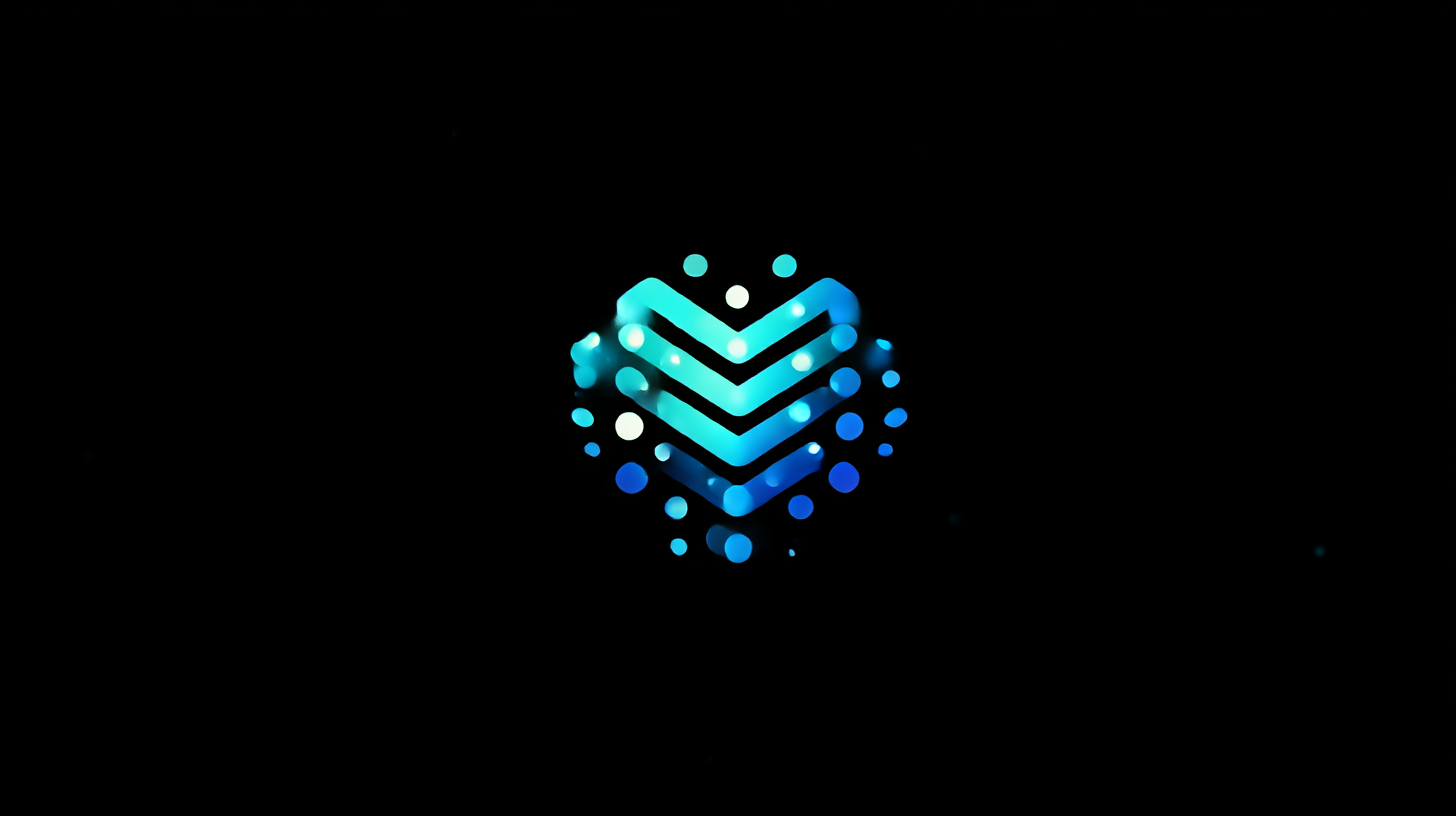
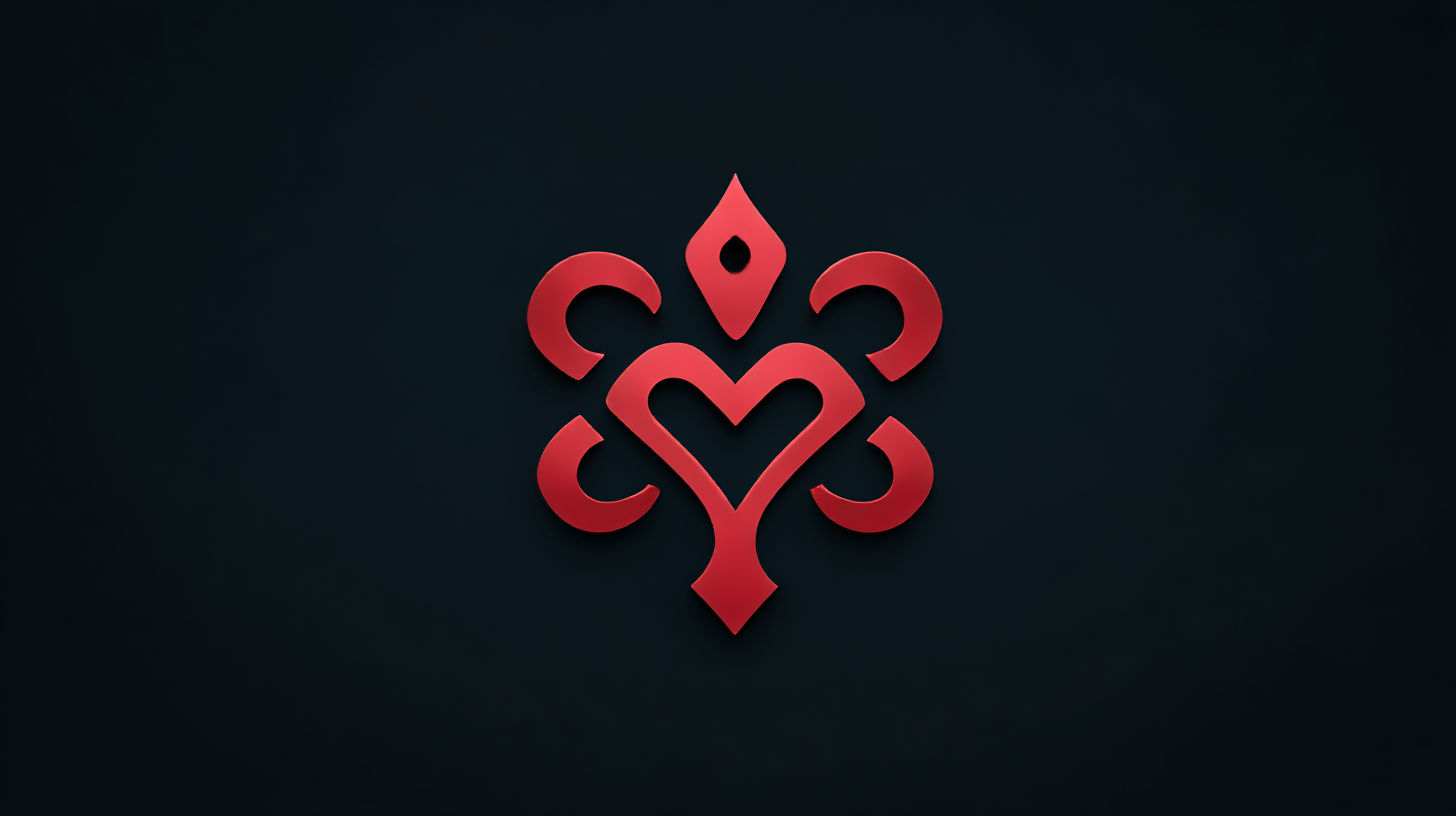
AI로 완성한 내 브랜드 로고 제작기 브랜드를 시작하려면 가장 먼저 떠오르는 게 로고예요. 감각적이고 기억에 남을 로고 하나로 브랜드 이미지가 확 달라질 수 있거든요. 그래서 저도 나만의 로고를 만들기로 결심했답니다. 그런데 문제는 디자인 경험이 전혀 없었다는 점이었어요.
고민 끝에 저는 AI의 힘을 빌리기로 했어요. 요즘은 디자이너 없이도 인공지능을 활용하면 퀄리티 있는 결과물을 만들 수 있다고 해서 시도해봤죠. 이 글에서는 제가 어떤 과정을 통해 브랜드 로고를 완성했는지, 그리고 AI가 어떻게 도와줬는지를 낱낱이 공개할게요! 🎨
이제 본격적으로 각 단계별 과정을 소개할게요. 로고 제작이 막막했던 분들이라면 제 경험이 큰 도움이 될 거예요. 그럼 같이 AI 디자인 여행, 시작해볼까요? 🖌
🎬 브랜드 로고 제작의 시작
처음 브랜드 로고를 만들겠다고 결심한 건, 제 사업 아이디어를 시각적으로 표현하고 싶어서였어요. 이름은 정했지만, 그에 어울리는 이미지를 떠올리는 건 생각보다 쉽지 않더라고요. 색깔은 어떤 톤이 좋을지, 심볼은 넣을지 말지조차 고민이 됐죠. 저는 미니멀한 감성을 좋아하긴 했지만, 너무 밋밋한 건 또 싫었어요.
그래서 로고 제작 웹사이트부터 유튜브 강의, 블로그 후기까지 정말 많은 자료를 찾아봤어요. 그리고 한 가지 확신이 생겼죠. 나 혼자 하긴 어렵겠다... 그때 눈에 들어온 게 바로 AI 로고 생성기였어요. 😲
AI 툴은 정말 다양했어요. Canva, Looka, Hatchful 등 몇 가지를 시도해보며 각각의 특징을 파악했죠. 간단한 설문을 통해 브랜드 성격을 입력하면 자동으로 여러 시안을 보여주는 방식이었어요. 첫 느낌은 "오, 이거 되게 괜찮은데?" 싶었답니다.
로고 스타일을 선택하고 나니, 색상 조합, 글꼴, 아이콘 등이 AI에 의해 제안됐어요. 그중 일부는 제가 상상하지 못한 창의적인 구성이기도 했고요. 이건 진짜 사람의 감각을 뛰어넘는다는 생각이 들었죠. AI랑 협업하는 기분이었어요. 🤖
🧠 사용한 AI 디자인 툴 비교표
🤖 AI가 도와준 창작 과정
로고 제작을 위해 Looka에 접속하자마자, 브랜드 이름을 입력하고 어떤 느낌의 브랜드인지 묻는 설문이 나왔어요. 선택지에는 ‘친근함’, ‘전문성’, ‘모던함’ 같은 키워드들이 있었고요. 저는 브랜드의 방향에 맞게 ‘따뜻함’, ‘신뢰감’, ‘세련됨’을 고른 다음, 색상도 고유 톤으로 블루 계열을 선택했어요.
그다음, AI는 30개 이상의 로고 스타일을 자동으로 추천해줬어요. 이 중에서 제 눈에 띈 건 둥근 텍스트에 간단한 아이콘이 포함된 로고였어요. 너무 화려하지 않으면서도 기억에 남는 디자인이라 첫 느낌부터 확 끌렸죠. 그걸 기준으로 몇 가지 다른 스타일도 섞어봤어요.
Looka는 선택한 로고를 기준으로 자동 조정 가능한 기능도 있었어요. 예를 들어, 텍스트 간격이나 아이콘 크기, 색상 톤의 채도를 미세하게 조정할 수 있었는데 이게 은근히 큰 차이를 만들어내더라고요. 디자인 감각이 없어도 시각적으로 딱 맞는 느낌을 고르기 좋았어요.
로고가 거의 완성된 이후엔 다양한 형태의 적용 예시도 보여줬어요. 명함, 웹사이트, 모바일 앱, 티셔츠 등에서 이 로고가 어떤 느낌으로 보일지를 실시간으로 확인할 수 있었어요. 이건 진짜 놀라운 기능이었고, 마치 실제 브랜드 오너가 된 것 같은 기분이 들었죠. 😍
🎨 AI 자동 추천 디자인 스타일 예시
스타일 설명 적용 예 미니멀 간결하고 직관적인 구성 IT, 패션 브랜드 빈티지 복고풍과 수제 느낌 강조 카페, 공방 타이포그래피 폰트 중심 디자인 출판사, 미디어 심볼형 로고 아이콘 강조 앱, 스타트업 이런 다양한 스타일 중에서 저는 ‘심볼형 + 미니멀’을 조합해서 최종 콘셉트를 잡았어요. 너무 화려하지 않으면서도 브랜드 정체성이 분명해 보여서 딱 좋았어요. AI 추천이 없었다면 이런 조합은 상상도 못했을 거예요. 이게 바로 기술의 힘이겠죠? 💡
🎯 디자인 요소의 선택 기준
AI가 제시해준 여러 로고 중에서 마음에 드는 스타일을 정한 후, 이제는 세부 디자인 요소를 하나하나 직접 조정해 나갔어요. 가장 먼저 선택한 건 폰트였어요. 브랜드의 느낌을 잘 살리려면 글자체가 정말 중요하거든요. 너무 각진 글꼴은 차가워 보이고, 너무 둥근 글꼴은 전문성이 떨어질 수 있었죠.
그래서 여러 번 테스트해보면서 ‘둥근 고딕체’ 계열을 최종 선택했어요. 딱딱하지 않으면서도 깔끔한 인상을 줄 수 있었거든요. 그리고 색상은 브랜드 톤에 맞춰 블루와 그레이 조합으로 조정했어요. 블루는 신뢰와 안정감을 상징해서 특히 금융이나 기술 분야에서 자주 쓰이기도 하죠.
심볼도 고민을 많이 했는데, 추상적인 아이콘보다는 제 브랜드가 다루는 핵심 개념을 직접 표현할 수 있는 그림 요소를 넣었어요. 예를 들어, 교육 관련 브랜드라면 책 모양의 아이콘을 넣는 식으로요. 직관적이고 쉽게 기억되기 때문에 심볼은 단순하면서도 의미 있는 게 좋아요.
여기서 중요한 건, AI가 추천해주는 기본값이 전부가 아니라는 점이에요. 추천값은 시작점일 뿐이고, 그 위에 내가 원하는 느낌을 더해가야 진짜 내 브랜드에 맞는 로고가 나와요. 저는 배치도 손봐가면서 상하 정렬보다는 좌우 배치가 더 보기 좋다는 것도 발견했답니다. 📐
🧩 디자인 요소별 선택 기준 요약
요소 선택 기준 추천 방향 폰트 브랜드 성격에 맞는 글꼴 고딕, 산세리프 계열 색상 심리적 상징성 고려 블루, 민트, 모노톤 심볼 직관적이고 간결한 이미지 주제 연관 아이콘 배치 가독성과 비율 좌우형 권장 디자인이란 게 단순히 예쁜 걸 만드는 게 아니라, 메시지를 시각적으로 전달하는 작업이라는 걸 새삼 느꼈어요. AI 덕분에 기본 틀은 쉽게 만들 수 있었지만, 그 위에 나만의 감성과 브랜드 철학을 얹어야 진짜 내 브랜드 로고가 되더라고요. 🎯
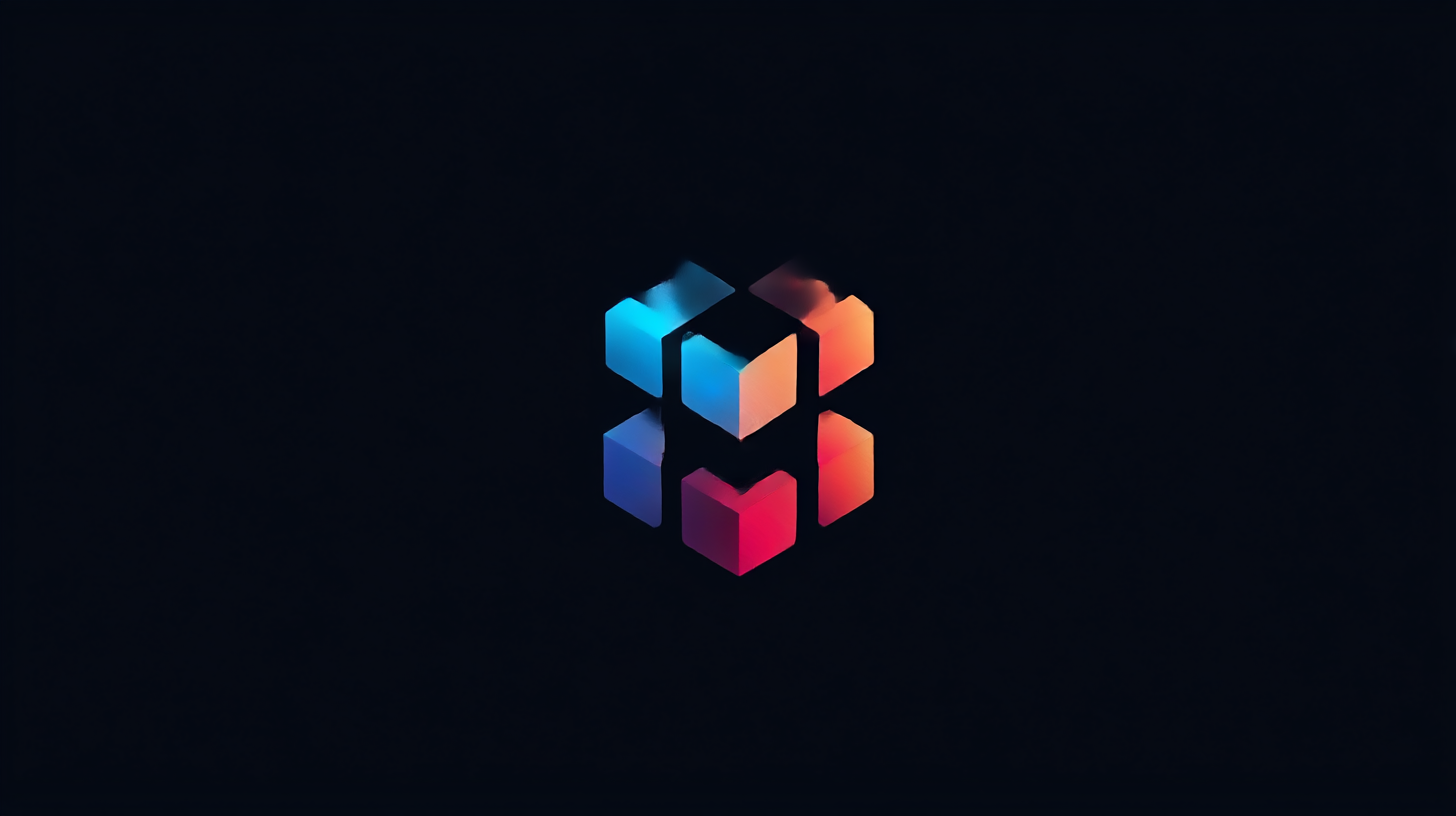
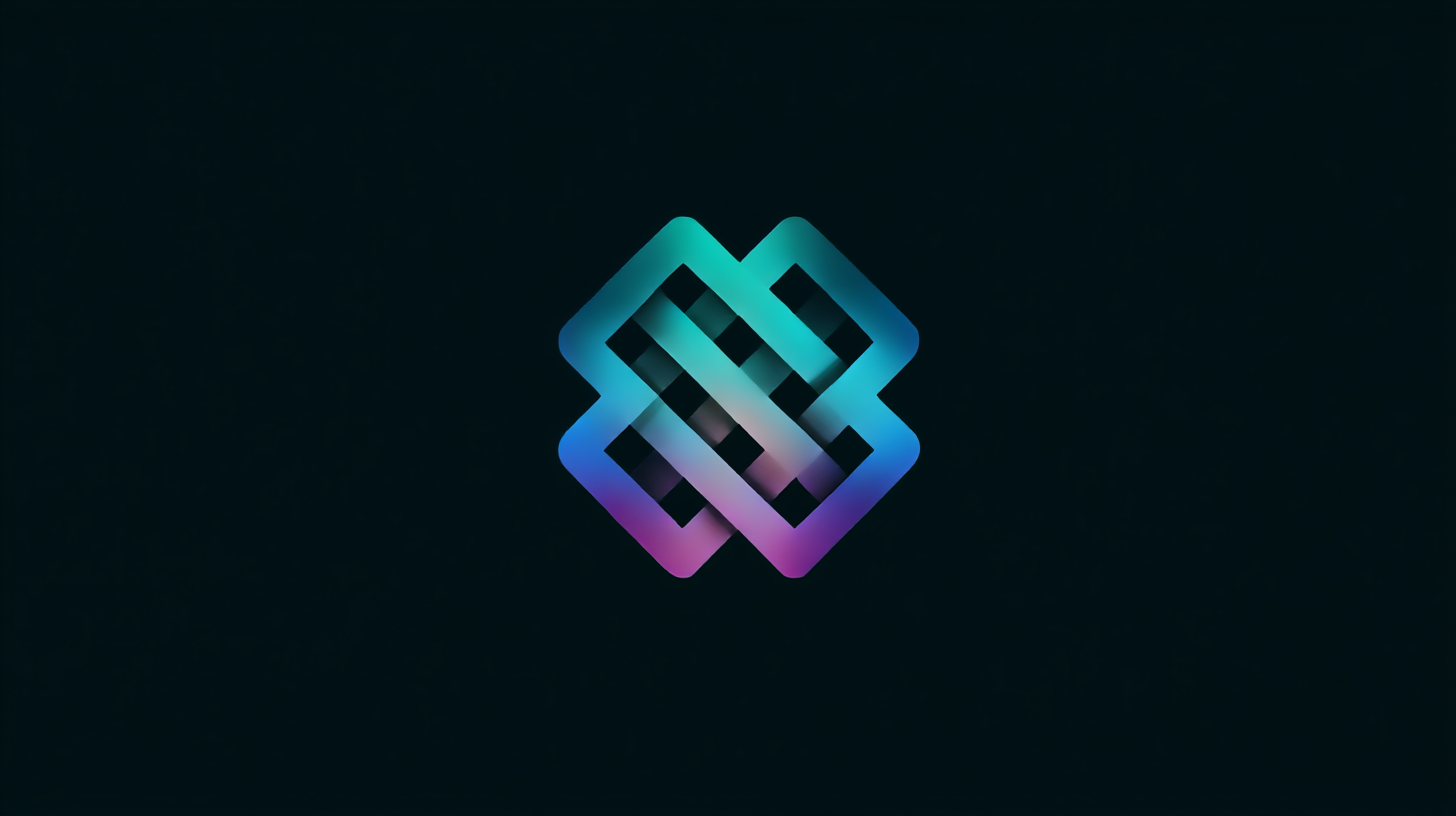
디자인 요소의 선택 기준 🔁 수정과 피드백 반복기
디자인이라는 게 한 번에 딱 나오는 경우는 정말 드물더라고요. AI가 만든 초안은 충분히 훌륭했지만, 그걸 그대로 사용할 수는 없었어요. 그래서 몇 차례에 걸쳐 수정 작업을 진행했어요. 혼자 보기엔 괜찮아 보였지만, 다른 사람들의 의견을 들어보니 전혀 예상 못 한 부분도 있었거든요.
가장 먼저 받은 피드백은 심볼이 너무 일반적이라는 것이었어요. 브랜드만의 정체성이 부족해 보일 수 있다는 말이었죠. 그래서 심볼을 좀 더 고유하게 바꾸고, 선의 두께나 각도를 조정했어요. 그렇게 조금씩 다듬어가는 과정이 반복됐죠. 이때 AI가 자동으로 변형된 여러 버전을 제시해줘서 선택이 쉬웠어요.
피드백 중 하나는 폰트에 관한 내용이었어요. 모바일에서 봤을 때 너무 작게 보이거나 선이 가늘어서 시인성이 떨어지는 문제가 있었죠. 그래서 조금 더 두껍고 단단한 느낌의 글꼴로 변경했어요. 이런 점은 실제 적용 화면을 미리보기 하지 않으면 알기 어렵더라고요. 이게 실제 적용이 중요한 이유예요.
색상도 작은 변화가 큰 차이를 만들었어요. 처음에는 회색 톤이 많았는데, 너무 무난해서 인상에 남지 않는다는 의견이 있었어요. 그래서 서브컬러로 산뜻한 민트를 추가하고, 포인트 요소에도 색상을 입혀봤죠. 결과적으로 훨씬 더 생동감 있는 로고가 됐어요. 이건 정말 '같은 로고인데 느낌이 다르다'는 말이 딱 맞았죠. 🎨
🔄 주요 피드백 & 수정 내용 정리표
피드백 항목 기존 상태 수정 방향 심볼 일반적이고 흔한 아이콘 브랜드 정체성 반영한 고유 아이콘 폰트 얇고 가독성 떨어짐 두껍고 안정감 있는 서체 색상 무채색 위주 포인트 컬러 추가 배치 상하형 조합 좌우형으로 변경 이런 수정 작업이 반복될수록 제 브랜드에 맞는 로고가 점점 구체화됐어요. 처음엔 단순히 ‘로고 만들기’였지만, 점점 ‘브랜드의 얼굴을 정립하는 작업’으로 느껴졌죠. 저는 이런 과정이 정말 소중하다고 느꼈어요. 디테일이 진짜 결과물을 만들어주더라고요. 😌
📦 최종 로고 완성과 적용
모든 피드백과 수정 과정을 거치고 드디어 ‘이거다!’ 싶은 로고가 완성됐어요. AI가 제안해준 디자인에서 시작해, 제 손으로 한 땀 한 땀 다듬은 결과물이었기 때문에 그 만족감은 더 컸어요. 로고를 처음 만들 때만 해도 이렇게까지 정이 들 줄 몰랐거든요. 😄
완성된 로고는 다양한 파일 형태로 저장했어요. PNG, SVG, PDF까지 제공되니 어디든 활용하기 좋더라고요. 특히 배경이 없는 PNG 파일은 SNS 프로필 사진이나 웹사이트 상단에 넣기에 딱이었고요. 크기별로 자동 저장돼서 모바일에서도 바로 적용 가능했어요.
로고를 실제 브랜드에 적용해보니, 드디어 사업이 눈에 보이는 형태를 가지기 시작했어요. 웹사이트 메인, 명함, 포장 박스, 홍보물 등 다양한 곳에 로고가 들어가니 브랜드의 정체성이 확실히 잡히더라고요. 특히 포장재나 티셔츠에 인쇄된 모습은 정말 감동이었어요. 🧢📦
이제는 로고 하나만 봐도 제 브랜드의 방향성과 가치가 느껴지는 것 같아요. 이걸 계기로 전체적인 브랜딩 전략도 다시 정비했어요. 로고에서 출발해서 브랜드 색, 글꼴, 톤앤매너까지 통일되니 일관된 인상을 줄 수 있었죠. AI 덕분에 이렇게 큰 그림을 다시 그리게 됐어요.
📁 로고 적용 분야별 활용 예시
분야 활용 예 사용 파일 형식 SNS 프로필, 커버 이미지 PNG 웹사이트 헤더, 파비콘 SVG, PNG 인쇄물 명함, 스티커, 포장지 PDF, EPS 제품 디자인 티셔츠, 머그컵 PNG, PDF AI와의 협업으로 시작한 로고 제작은 제 브랜드에 생명력을 불어넣는 경험이 됐어요. 이제는 이 로고가 담긴 제품이나 페이지를 볼 때마다 스스로 대견한 마음도 들고, 정말 ‘내 브랜드’를 만든 느낌이 들어요. 💙
Q4. 직접 디자이너에게 맡기는 것보다 어떤가요?
A4. 예산이 적고 빠르게 결과가 필요한 경우엔 AI가 훨씬 유리해요. 하지만 완전히 맞춤형 디자인이 필요하면 디자이너와의 작업도 고려해보세요.
Q5. 로고 수정은 자유롭게 할 수 있나요?
A5. 대부분의 AI 로고 생성기는 로고 생성 후에도 색상, 글꼴, 배치 등을 자유롭게 수정할 수 있는 에디터 기능을 제공해요.
Q6. 무료로 사용할 수 있는 AI 툴도 있나요?
Q7. 로고 외에도 AI가 다른 디자인도 도와주나요?
A7. 맞아요! 명함, 배너, SNS 포스트, 브랜드 키트까지 제공하는 AI 서비스도 있어서 전체 브랜딩도 도와준답니다.
Q8. 초보자도 쉽게 사용할 수 있나요?
A8. 대부분 직관적인 UI로 구성되어 있어서 초보자도 쉽게 접근할 수 있어요. 클릭 몇 번이면 로고 시안을 볼 수 있을 정도로 간편하답니다!